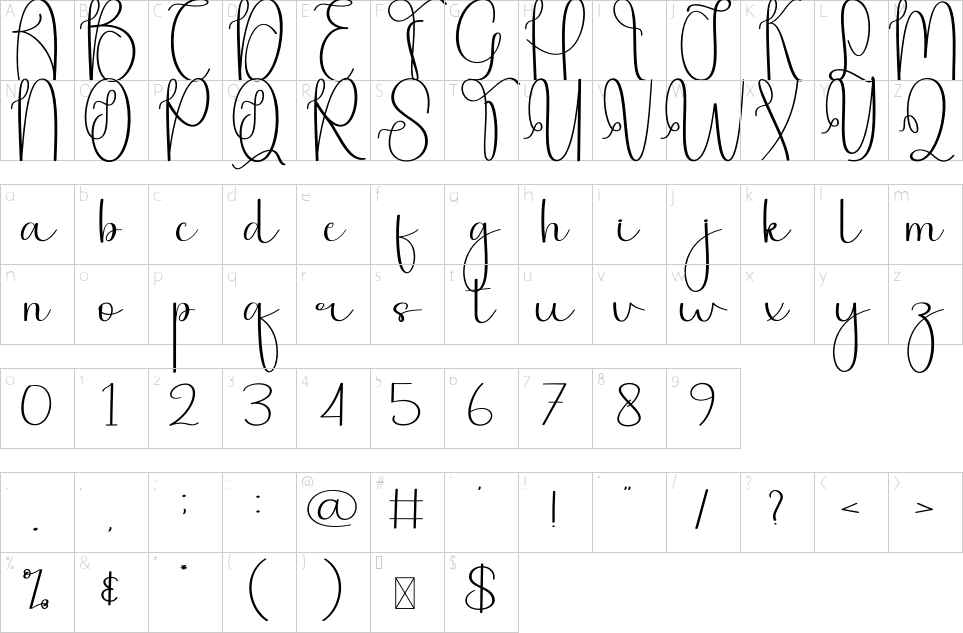
Descubra Ginger Bread Font para Windows e Mac aqui. Desenvolvida por William Jhordy, esta fonte grátis é ideal para designers que buscam uma opção moderna e enérgica. Com seu design minimalista e elegante, a Ginger Bread traz um toque fresco às suas criações digitais. Oferecida em formato gratuito, essa fonte conta com um sucesso contínuo de downloads, sendo baixada cerca de 365 vezes. Ideal para aplicar em elementos gráficos como títulos e headlines, a Ginger Bread adiciona uma cara jovial e divertida aos seus designs digitais. Experimente agora e adicione alegria ao seu trabalho com esta fonte única e versátil.